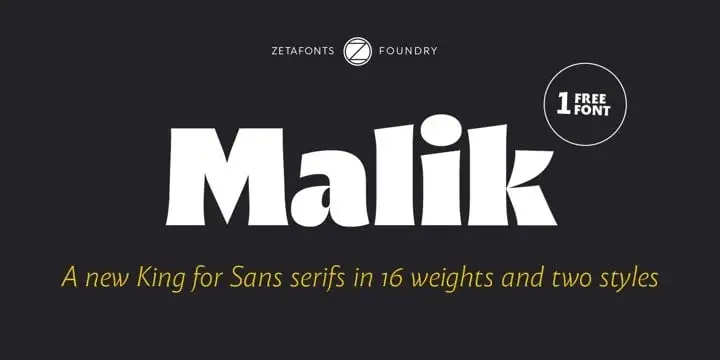
Malik Serif Font
A Malik Serif é uma fonte serif masculina que combina elegância clássica com habilidade modernista, revelando influências do calligrafia dos mestres contemporâneos Frederic Goudy e Ed Benguiat nos detalhes de sua assinatura. Esses detalhes notáveis incluem um B maiusculo reverso contrastante que evidencia essa tradição moderna, bem como o k minúsculo inspirado na calligrafia, adicionando uma sensação única ao seu uso. Seja para anúncios de moda ou capas de livro, a Malik Serif oferece um equilíbrio perfeito entre elegância e modernidade, trazendo a personalização que seu design precisa. Opte por essa fonte elegante quando desejar adicionar uma dimensão única à sua identidade visual.